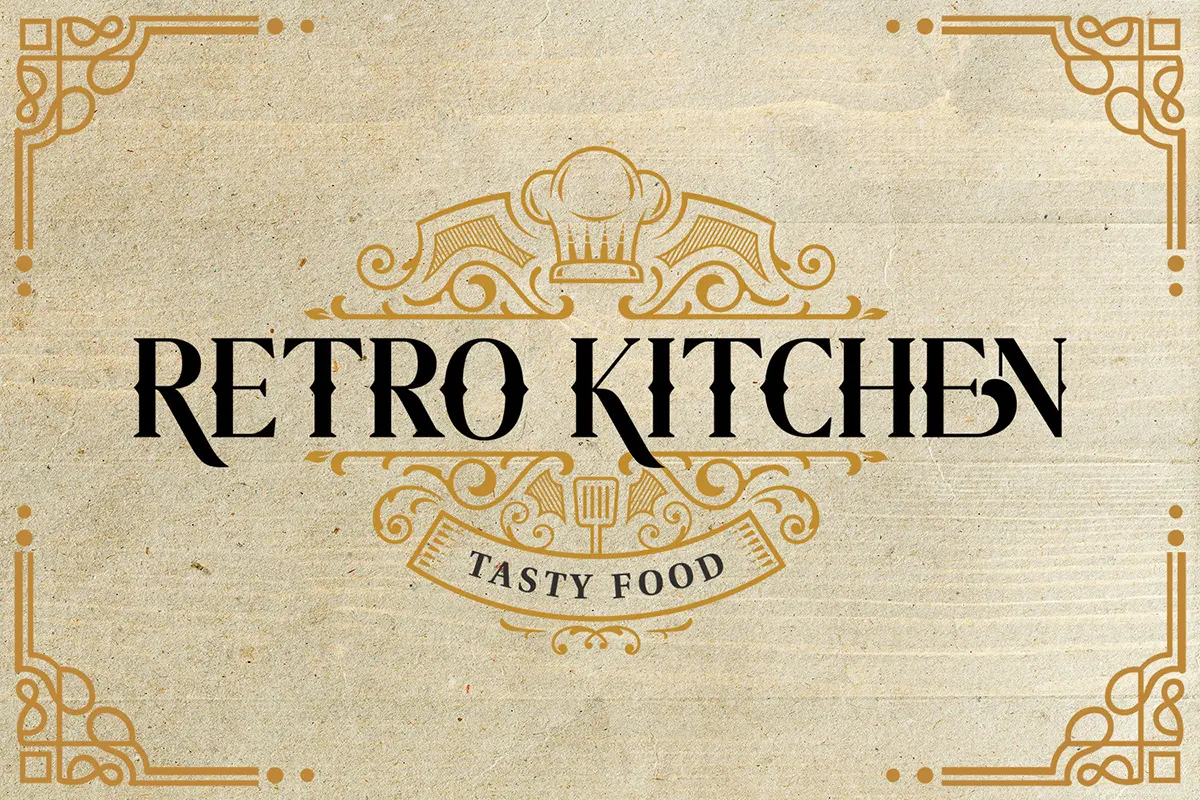
فونت کلاسیک و وینتیج
فونت The Cheelaved یک تایپفیس نمایشی (Display) با سبک سریف وینتیج است که الهامگرفته از جنبش هنرهای تزئینی و معماری کلاسیک طراحی شده. این فونت با خطوط قدرتمند و جزئیات ظریف، حس اصالت و شکوه را به طراحیهای شما اضافه میکند و برای پروژههایی که نیاز به جلوهای تاریخی، رسمی یا هنری دارند انتخابی عالی است.
⭐ ویژگیهای کلیدی
- سبک سریف وینتیج با الهام از هنرهای تزئینی
- مناسب برای تیترها و طراحیهای نمایشی
- قابل استفاده در پروژههای چاپی و دیجیتال
- ترکیب ظرافت و قدرت در حروف برای ایجاد حس کلاسیک
🎯 موارد استفاده پیشنهادی
- طراحی پوسترهای هنری و تبلیغاتی
- ساخت لوگوهای رسمی و کلاسیک
- طراحی بج و لیبلهای قدیمی
- استفاده در تیشرتها و محصولات چاپی
- طراحی گواهینامهها و کارتهای رسمی
- مناسب برای پستهای شبکههای اجتماعی با حالوهوای وینتیج